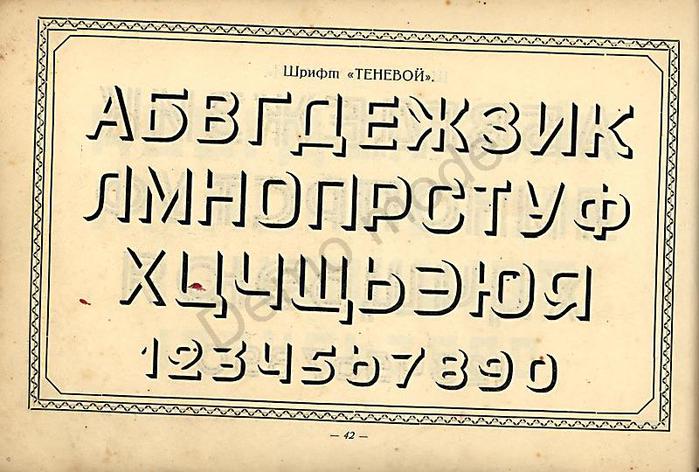
ЗАКЛЮЧЕНИЕ
Мы проследили развитие графики русского типографского шрифта
на протяжении 250 лет. Мы видели, как на определенных этапах его
развития в России создавались шрифты, отражавшие веяния той или
иной эпохи. Перед нами прошли работы замечательных мастеров: гра¬
веров XVIII века, граверов, типографов и издателей первой и отчасти
второй половины XIX века. Советские художники и мастера шрифтов
являются наследниками всего лучшего, что было сделано в этом на¬
правлении в России.
При изучении истории развития русского гражданского шрифта осо¬
бого внимания заслуживает его первоисточник — шрифт, утвержден¬
ный Петром I в 1710 году. Большой интерес представляют для нас
не только лучшие образцы гражданских шрифтов петровского пери¬
ода, но и опыт построения алфавита этих шрифтов.
Важным этапом в развитии типографского дела в России было
создание нового гражданского шрифта типографией Академии наук
40-х годов XVIII века.
словолитне Академии наук при участии лучших граверов XVIII ве¬
ка Ивана Соколова и Григория Качалова. Лучшие из этих шрифтов
даны в печатных образцах типографии Академии наук 1748 года. Из
них отметим титульный — малый канон, из текстовых — парагон ан¬
тиква и гробе цицеро и из курсивов — парагон антиква курсив.
Шрифты типографии Московского университета конца XVIII ве¬
ка отражают переходный период в развитии графики русского шриф¬
та. Наиболее интересен из них круглый миттель из образцов типо¬
графии Московского университета 1796 года.
На грани XIX века оригинальные русские шрифты создавались
шрифты этих мастеров даны в образцах Бодони 1818 года и Дидо
1814 и 1828 годов.
В первой четверти XIX века в русских типографиях устанавли¬
ваются два рисунка шрифтов: московский и петербургский. Шрифты
эти представлены в образцах словолитни Бекетова 1805 года.
Из них
следует отметить титульные шрифты большой кз.нон* пярягон прямой
и терция петербургского и московского вариантов.
Становление московского варианта в текстовых и титульных шриф¬
тах первой четверти XIX века отражается в продукции лучших сло¬
образцов Селивановского больше всего заслуживают внимания титуль¬
ные шрифты (двойной миттель — прямой и курсив, канон малый,
миссаль малый), а также текстовые — терция и цицеро с курсивом
московского варианта; из образцов Семена петит парагон с курси¬
вом и цицеро с курсивом.
Особо интересный материал для изучения и использования пред¬
ставляют образцы шрифтов, орнаментов и политипажей словолитного
заведения Ревильона 1837—1849 годов. Из шрифтов Ревильона особого
внимания заслуживают различные варианты обыкновенного, английские
шрифты и целый ряд декоративных. Английский шрифт словолитни
Созданные в 60-х и 70-х годах новый газетный шрифт, а также шриф¬
ты для художественной литературы (шрифт газеты «Современная ле¬
топись» 1861 года, а также шрифт эльзевир словолитни Вольфа) не
получили сколько-нибудь широкого распространения.
Из титульных шрифтов заслуживают внимания образцы типографии
Академии наук 1870 года, которые всегда отличались чистотой нарезки.
К ним прежде всего относятся различные варианты так называемых
обыкновенных шрифтов.
Шрифты конца XIX и начала XX века создавались в основном под
ценности. Вместе с тем в образцах Бертгольда заслуживают внимания
всем известные латинский и академический, а в образцах Лемана ели¬
заветинский.
Советские художники при создании новых рисунков типографских
шрифтов, обращаясь к образцам прошлого, использовали главным обра¬
зом шрифты первой половины XVIII века, особенно петровского перио¬
да.
Следует указать, что в этом плане несомненно заслуживают вни¬
мания лучшие образцы рисунков шрифтов второй половины XVIII и
первой половины XIX века (например, типографии Академии наук,
74. Шрифтовые формы XIX века
До конца XVIII века различия между книжными, рекламными и газетными шрифтами не существовало, употреблялся один и тот же шрифт, но разного размера. С активным развитием промышленности и торговли в XIX веке начали возникать новые стили шрифтов для газетных объявлений, рекламы и других акцидентных (т.е. выполняемых по случайным, разовым заказам) работ. Эти шрифты отличались от книжных особым, бросающимся в глаза рисунком. Эксперименты в области шрифтовой формы привели к возникновению новых видов шрифта.
К таким акцидентным шрифтам принадлежит появившийся в начале XIX в. египетский или брусковый шрифт
Отличительным
признаком этого шрифта является
одинаковая толщина всех линий и засечек
букв.
При этом пропорции и расположение
засечек такие же, как у антиквы. Существуют
разновидности египетского шрифта с
большим или меньшим различием в
насыщенности основного и дополнительного
штриха. Известнейшие из типографских
Оси округлых
знаков прямые.
Как правило, имеют
большое количество начертаний
различных пропорций и насыщенности.